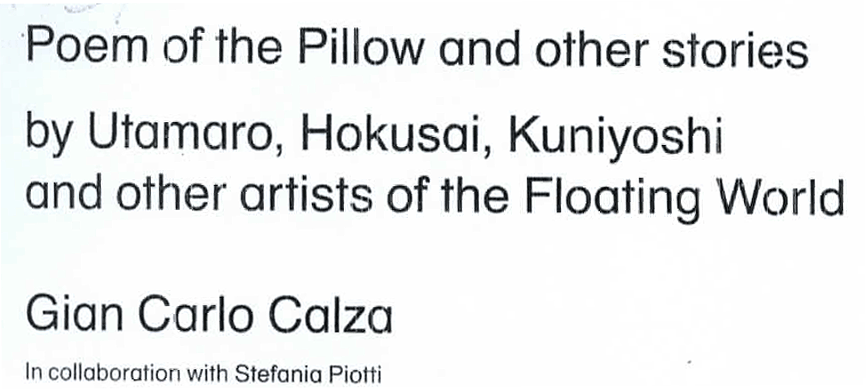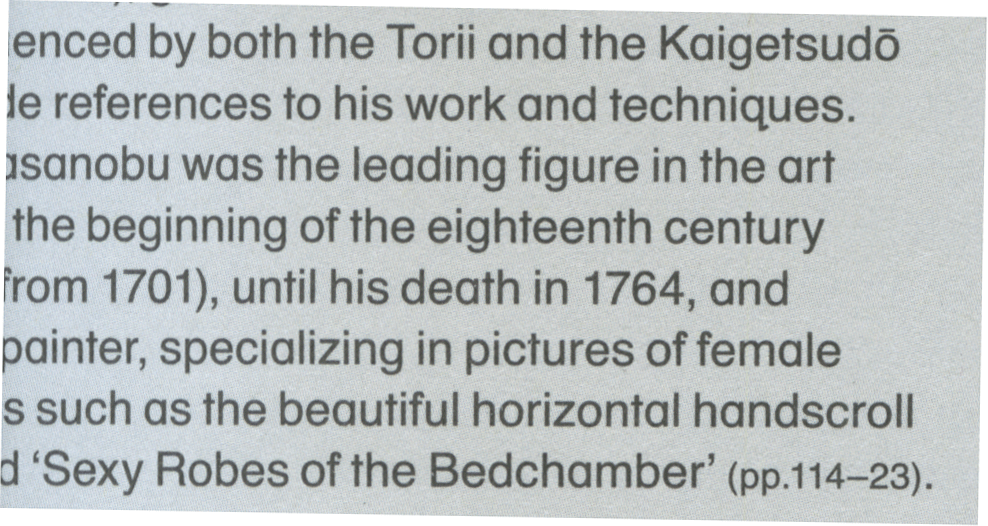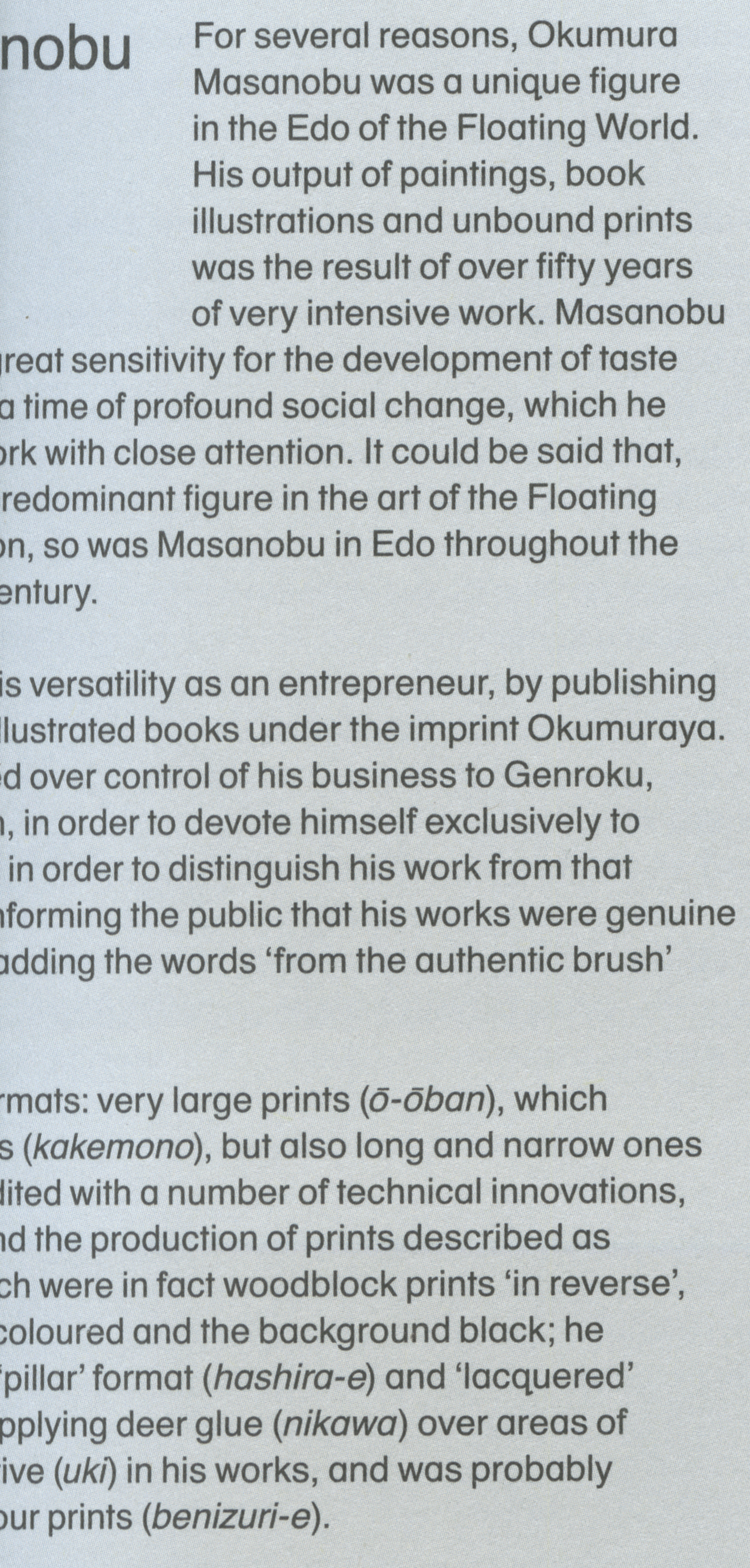
Schrift aus Phaidon-Buch
Dachte erst, es wäre die FF Schulbuch – bis ich das ("US-Schul"-) q mit dem Haken und das Kreuzchen-t gesehen hab. :-(
Die Helvetica Textbook ist – bis hin zum q – schon einmal ein guter Treffer, wären da nicht noch das I, das J oder die Ziffern 1 , 4 und 6…